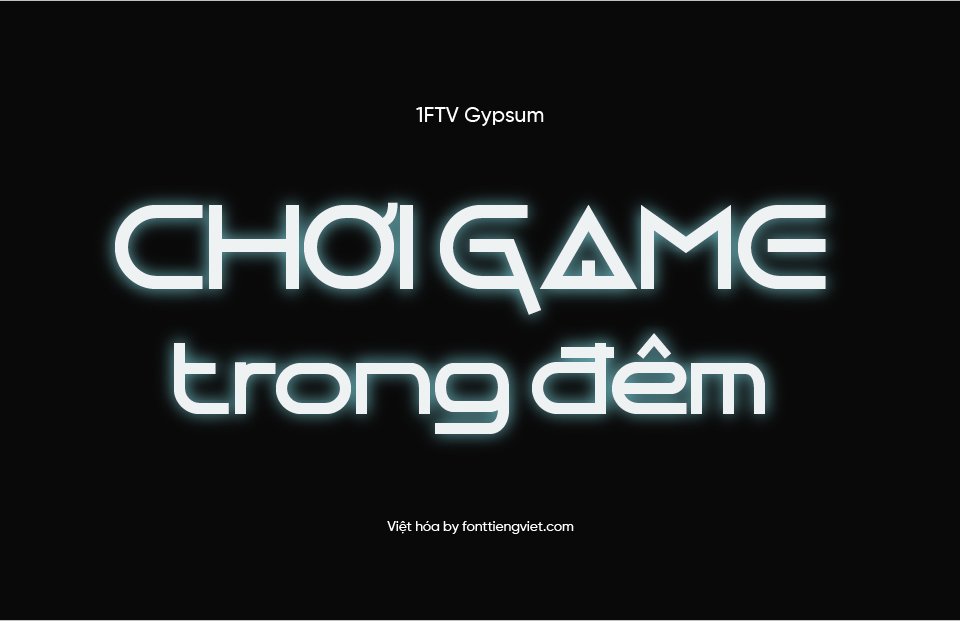
Font Việt hóa 1FTV Gypsum
Giới thiệu về Font Việt hóa 1FTV Gypsum
Trong thế giới thiết kế đồ họa dành cho học đường, việc lựa chọn một Font Miễn Phí phù hợp đóng vai trò cực kỳ quan trọng. Font Việt hóa 1FTV Gypsum nổi lên như một giải pháp hoàn hảo cho những ai đang tìm kiếm sự kết hợp giữa nét hiện đại và tính ứng dụng cao. Bộ phông chữ này không chỉ giữ nguyên được linh hồn của thiết kế gốc mà còn được tối ưu hóa hoàn toàn cho bảng mã tiếng Việt, giúp người dùng không còn lo lắng về lỗi hiển thị dấu câu hay ký tự đặc biệt.
Đặc điểm nổi bật của bộ Font Việt hóa 1FTV Gypsum
Được lấy cảm hứng từ những khối thạch cao vững chãi, Font Việt hóa 1FTV Gypsum sở hữu những đường nét mạnh mẽ, rõ ràng nhưng không kém phần mềm mại ở các góc bo. Điều này tạo nên một cảm giác thân thiện, cực kỳ phù hợp cho các bài giảng trình chiếu, poster sự kiện trường học hoặc tiêu đề các báo cáo dự án của học sinh. Sự cân bằng trong khoảng cách chữ giúp người đọc dễ dàng theo dõi nội dung từ xa mà không gây mỏi mắt.
Cách ứng dụng Font Việt hóa 1FTV Gypsum hiệu quả nhất
Để tận dụng tối đa vẻ đẹp của bộ chữ này, các bạn nên sử dụng chúng cho các tiêu đề chính hoặc các đoạn trích dẫn quan trọng. Việc kết hợp Font Việt hóa 1FTV Gypsum với các tông màu sáng hoặc màu pastel sẽ giúp trang thiết kế trở nên sinh động và thu hút hơn. Đây là công cụ đắc lực giúp thầy cô giáo đổi mới giáo án điện tử, tạo hứng thú học tập cho các em học sinh qua từng slide bài giảng đầy tính thẩm mỹ.